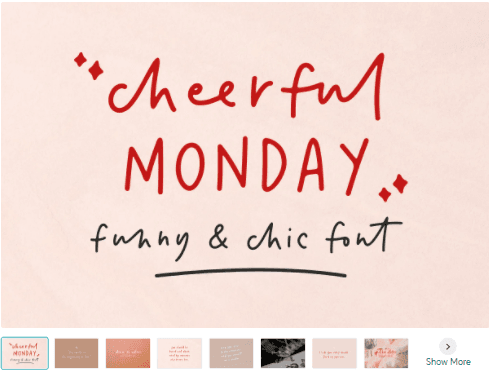
Cheerful monday font
Представляем вам веселый понедельник, рукописный шрифт, который имеет 2 варианта (обычный и полужирный), и для улучшения вашего письма мы предлагаем 72 лигатуры на ваш выбор, чтобы резюмировать сделанные слова / предложения, а также снабжены каракулями в качестве бонуса. Идеально подходит для дизайна цитат, причудливых логотипов, продуманной упаковки, вывесок, поздравительных открыток, дизайна товаров и многого другого!